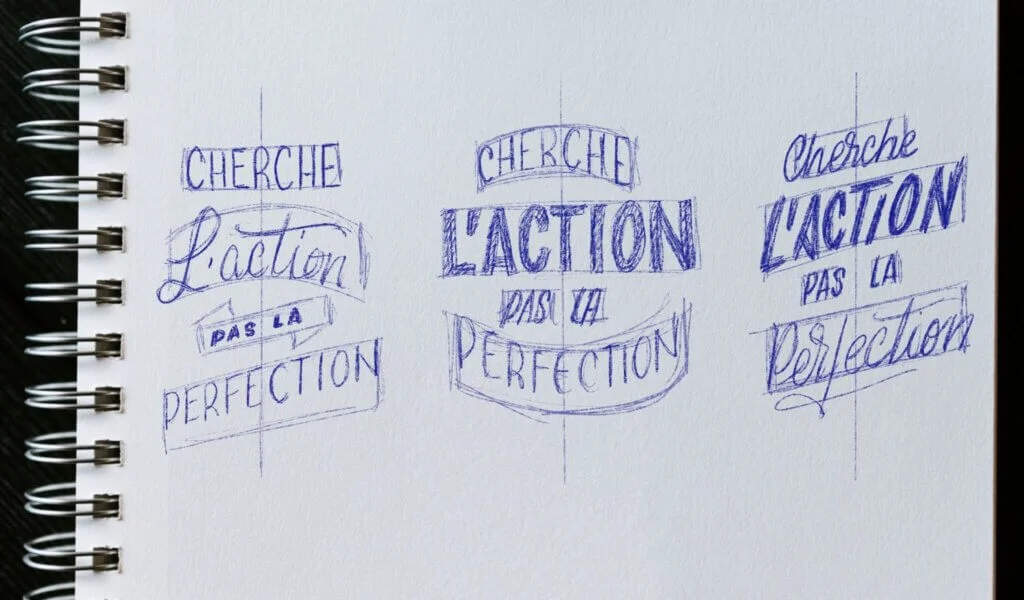
Un exercice de lettering facile pour composer une phrase en lettering, ça te dit ? Heureuse coïncidence : c’est le sujet du jour. Aujourd’hui, je te propose d’apprendre à structurer et harmoniser tes compositions pour dessiner des phrases en lettrage impactantes. Tu vas prendre confiance en tes dessins de lettres. Surtout, tu vas dire adieu aux compositions bancales que tu ne sais pas corriger. A l’issue de ces 5 étapes, tu sauras composer une phrase en lettering autour d’un axe central, promis !
Rebouche tes feutres et sors tes pinceaux de l’eau avant qu’ils ne s’abîment, tu as plusieurs notions à comprendre avant de dessiner ta première phrase en lettering !
Je ne veux pas faire la rabat-joie, seulement t’aider à créer et composer un lettrage harmonieux et stylé.
Déjà, nous allons commencer par choisir une phrase.
Je te partage l’une de mes préférées. C’est mon leitmotiv au quotidien, au travail comme à la vie :
Cherche l’action pas la perfection.
La première étape, c’est de se dire : « Ok, qu’est-ce que je veux mettre en avant ? »
C’est impératif ! Si tu ne décides pas quels mots seront plus gros que les autres, toute la phrase en lettering va être sur la même hauteur de lecture et ça n’aura pas d’impact.
On hiérarchise le niveau de lecture des mots.
Ici, ce qu’on veut, c’est mettre en avant le mot « perfection » et le mot « action » qui s’affrontent dans la phrase. En tout cas, c’est ce que je décide de faire !
« Cherche » arrive derrière avec une hiérarchisation en dessous des mots « Action » et « Perfection ». Quant à « pas » et « la », ils sont vraiment très secondaires et arrivent donc en dernier, par ordre d’importance pour composer la phrase en lettering.
Moi, ce que j’aime bien faire après, c’est aussi compter le nombre de lettres parce que ça me permet de me donner une idée dans l’espace.
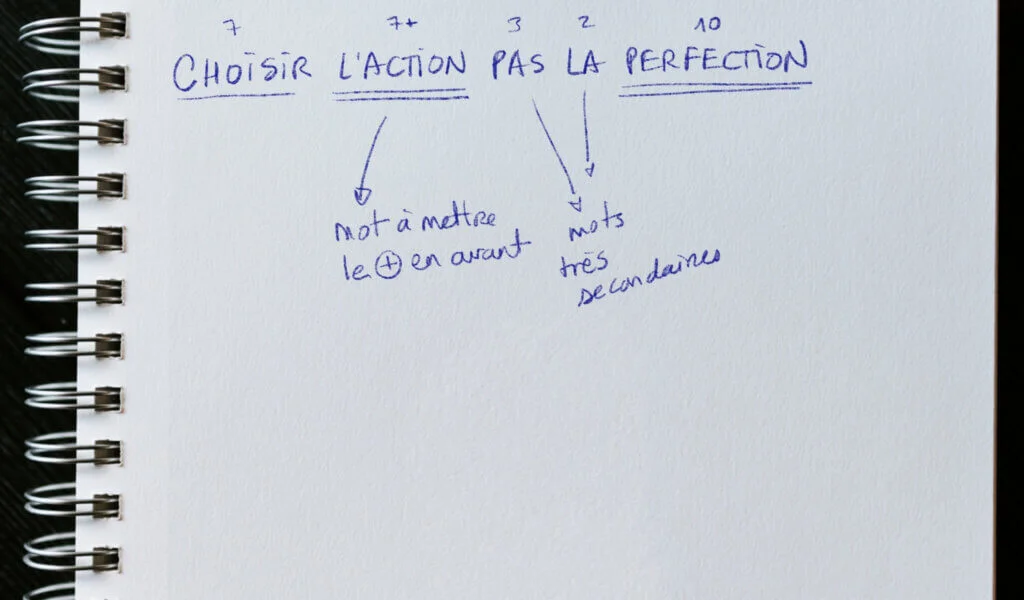
L’étape suivante va consister à simplifier les mots en formes, selon la hiérarchisation de lecture qu’on a choisie.
Quand on commence son lettrage, je trouve plus simple de symboliser les mots par des formes diverses pour me représenter dans l’espace leur prise sur la feuille.
Ici, je prends le parti de les représenter par des rectangles.
Si on reprend notre logique pour composer une phrase en lettering simple et harmonieuse, les rectangles vont croître en taille au fur et à mesure du degré de lecture de chacun des mots.
Donc :
Teste et vois ce qui fonctionne pour toi.
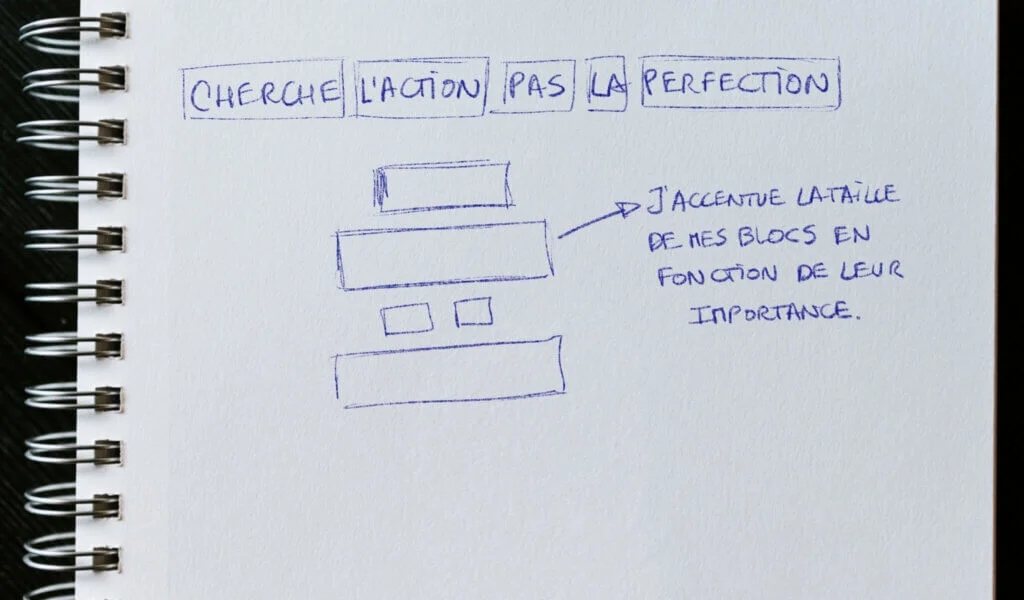
Ma promesse, c’est de vous apprendre à composer une phrase en lettering harmonieuse et simple autour d’un axe central.
Donc, on trace notre axe central : c’est notre point de départ.
Pour homogénéiser le tout, le mot-clé c’est : équilibre.
En clair, il faut avoir autant d’espaces à droite qu’à gauche.
Même si ta forme générale, où tu dessines ta phrase en lettrage, est un rond, c’est pareil : il faut harmoniser les éléments à droite et à gauche, autour de ton axe central.
Et cette logique se retrouve avec nos éléments graphiques.
Par exemple, si tu dessines ton mot dans un ruban, l’espace que va occuper le ruban d’un côté de ton axe central devra être, plus ou moins le même, de l’autre côté.
C’est le même principe pour chaque élément graphique que tu ajouteras à ta composition.
Bref, c’est le principe de la symétrie.
Tu reprends tes formes de l’étape 2 et tu les distribues sur l’axe central.
En débutant par les formes, on voit déjà comment résoudre les problèmes de composition, comme avec notre ruban.
Résultat ? C’est plus harmonieux.
C’est une composition classique !
Mais, après ces bases, rien ne t’empêche d’apporter des éléments graphiques de ton choix ou des ornementations sympas. Ce que tu veux, quoi ! Fais-toi plaisir.
La seule règle de l’exercice : il faut qu’il y ait un équilibre.
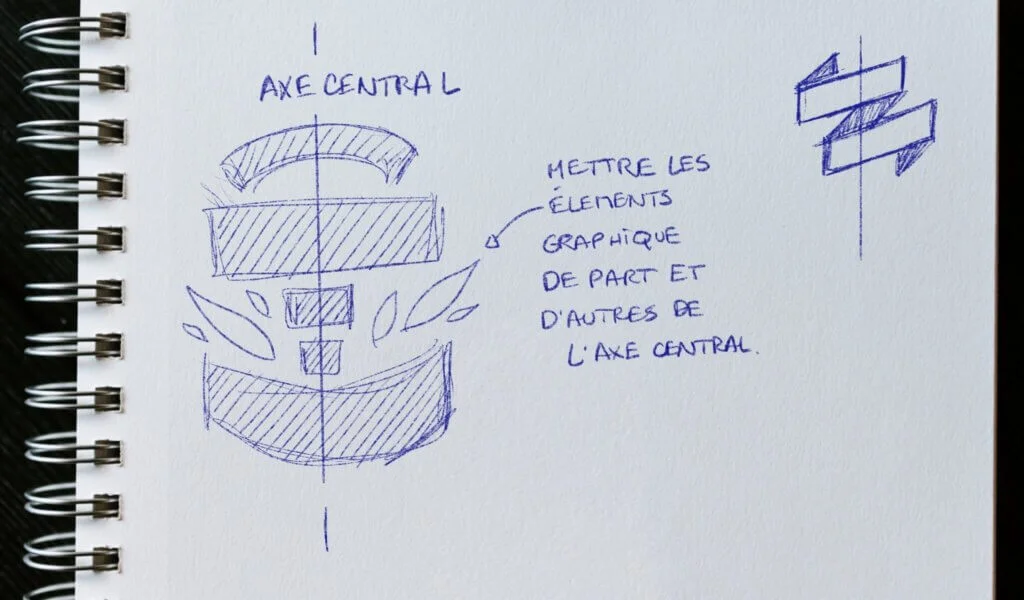
Voici déjà un exemple pour illustrer cette notion d’équilibre.
Si j’ai une majuscule «M» à droite et que j’ai une sortie en S (la dernière lettre de notre phrase), je dois penser à une ornementation pour compenser la taille imposante de ma première lettre : ça pourra être des petits éclairs, des illustrations florales…
Bref, tu peux toujours « tricher » avec des éléments graphiques pour harmoniser la composition de ton lettering.
D’où l’importance de se rappeler qu’on travaille sur un axe central et qu’on cherche à dessiner une composition harmonieuse avec autant d’éléments à droite qu’à gauche.
Une phrase en lettering harmonieuse, c’est une phrase qui a de la force et de l’impact.
Pour notre phrase « Cherche l’action pas la perfection », j’équilibre le P, qui est quand même une grande lettre. Volontairement, je décide de dessiner une sortie de N un peu grosse. Il faut juste que la boucle soit à peu près identique à celle du P pour compenser.
Ainsi, ça équilibre la composition.
Tente plusieurs compositions : déplace les formes, mets-les en diagonale, varie leur grosseur, dessine plusieurs éléments graphiques et vois ce qui te plait.